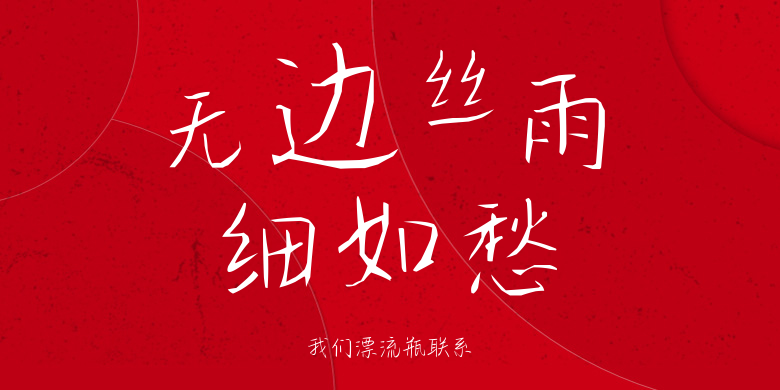
我们漂流瓶联系
我们漂流瓶联系,这款字体结构工整、笔画清晰,兼顾美观与易读性,适用于标题、正文、海报、包装、LOGO 等多种场景。字形优雅稳定,风格百搭耐看,适配日常排版与创意设计,让文字呈现更舒适、更具质感。我们漂流瓶联系一笔一画,皆是细节,以均衡的比例、流畅的线条打造舒适视觉体验,字形端正大气,风格简约现代。无论是商业设计、品牌宣传还是日常排版,都能轻松驾驭,让文字更有格调与力量。我们漂流瓶联系字体下载。